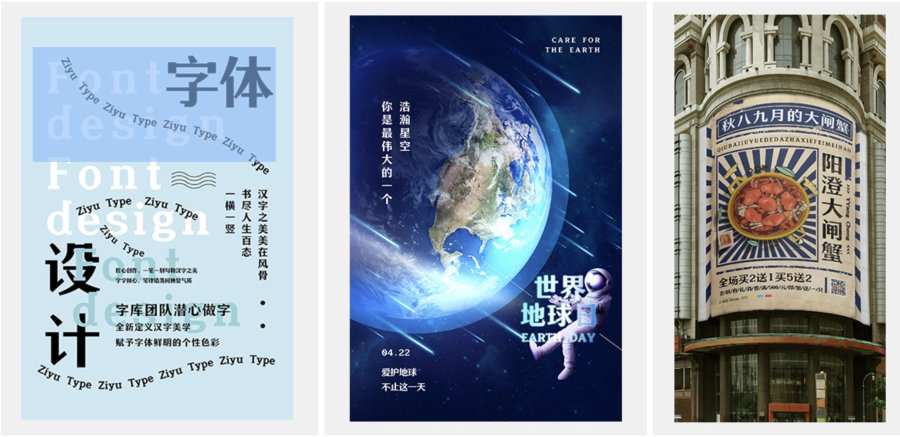
字语咏怀体 是一种字面较大、结构严谨的字体,它的特点使得它在各种应用中脱颖而出。这款字体的独到之处在于其厚重醒目的外观,字形设计精简有力,勾划捺划的舒展张力让人印象深刻。
字语咏怀体的应用广泛,特别适用于书法作品、标题设计和标志制作。其字面较大、布白均匀、重心平稳的特性,使得文字在排版中具备强烈的视觉冲击力,能够吸引人们的目光。同时,字体的笔形设计简洁有力,收笔处灵巧,使得它成为表达情感和思想的理想选择。